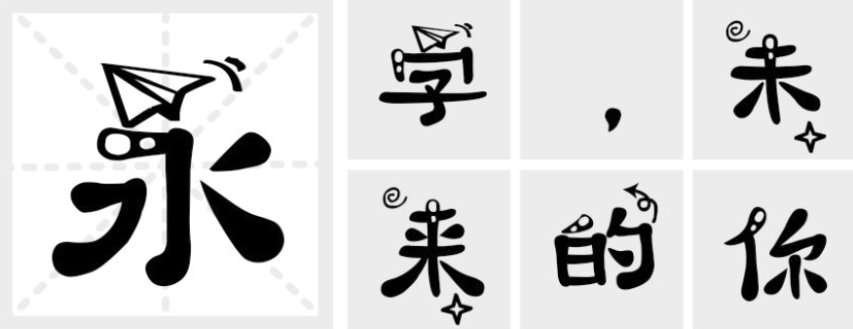
天秤座字体是在义启猪猪体上展开装饰而成 ,选用 了星星 、风筝 等可爱图案,使得静态文字有着buingbuing 的闪亮艺术之美 ,让每个星座的朋友都能拥有一款专属字体,更加突显个性。让你专享十二星座字体的幸福感,
也叫天平座,为人热情,优雅,善于表达。但常年伴有纠结症,事事要求平衡,是十二星座里最害怕孤独的一个。出生于9月23日—10月23日,为黄道十二宫之第七宫。